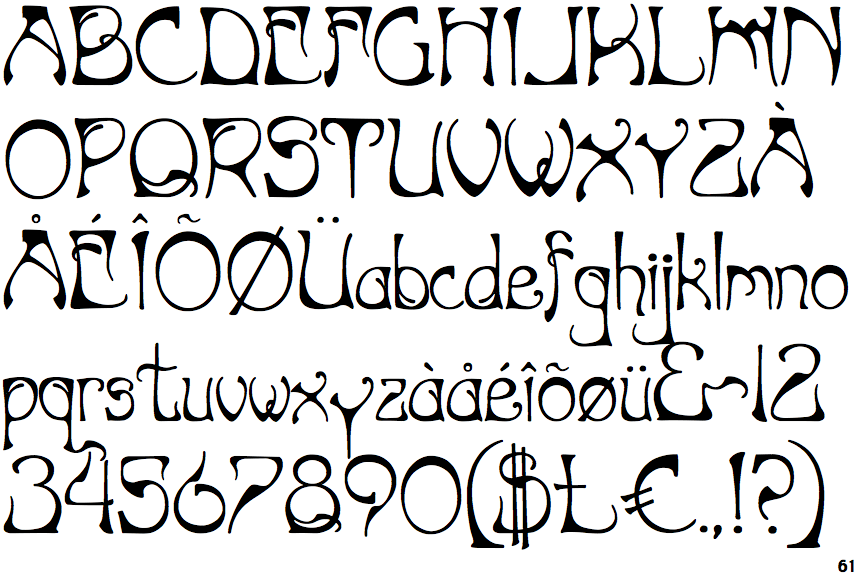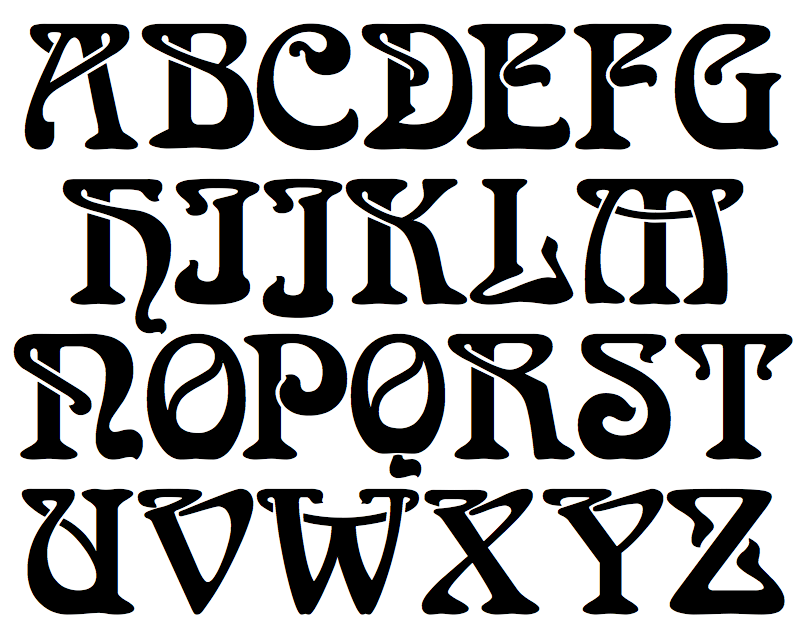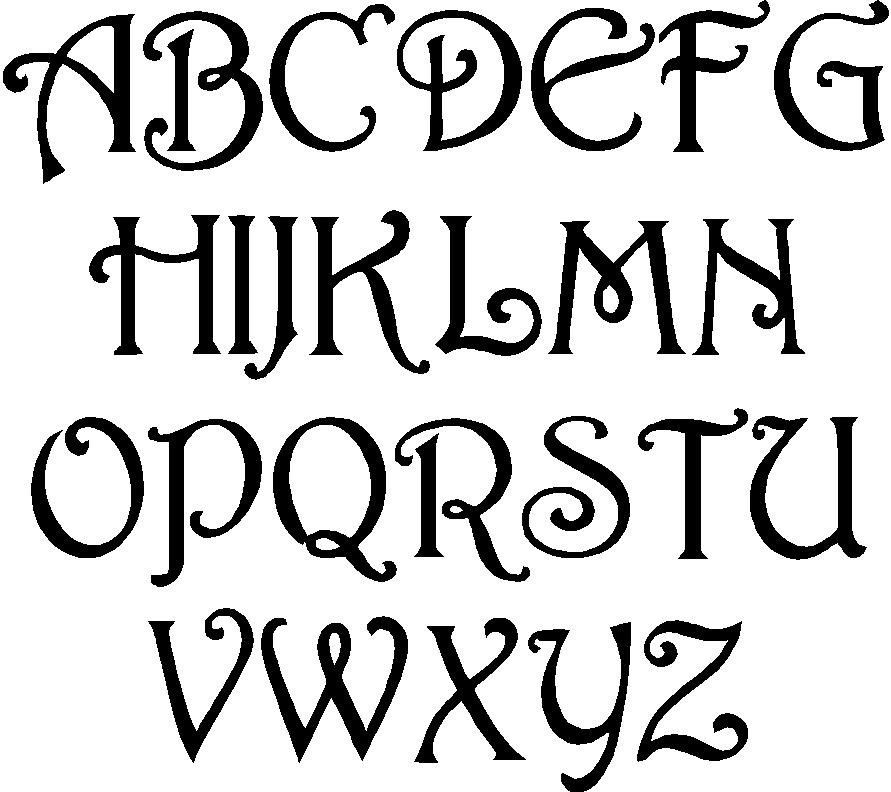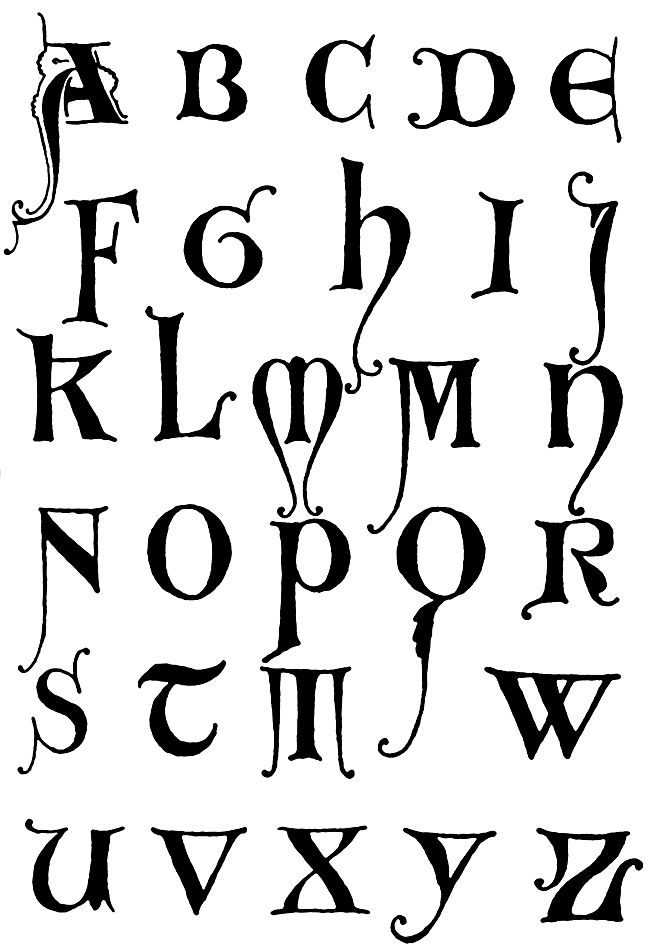
какие бывают и как выбрать
Шрифты для дизайна имеют первостепенную важность, ведь именно через них передаются настроение и голос любого креатива. Качество и изысканность дизайна во многом определяются выбранными шрифтами. К тому же не стоит забывать и об их прямой задаче – донесение информации до окружающих.
Таким образом, необходимость верного выбора шрифта очевидна, но для этого важно знать определенные правила. В нашей статье мы расскажем, какие их виды существуют и определим критерии, по которым стоит выбирать шрифты для проекта.
Понятие шрифта в дизайне
Термин «шрифт» в сфере дизайна применяется довольно часто. Чтобы лучше разобраться в данной теме, необходимо выделить три понятия: шрифт, гарнитура и вид шрифта.
Давайте подробно это рассмотрим.
- Гарнитура – это семейство начертаний шрифта, которые имеют общие стилевые особенности. Например, популярные Arial и Garamond – это гарнитуры, в которых присутствует набор различных вариантов: жирные, полужирные, курсивные и другие шрифты.
- Шрифт – это определенное начертание в рамках гарнитуры, а также файл со специальным разрешением, который нужно скачать на компьютер и установить в операционную систему. К примеру, Arial Italic и Garamond Bold являются шрифтами.
- Чтобы вам легче понять разницу в терминах, можете использовать такую аналогию: гарнитура – это фамилия, а шрифт – имя. К примеру, Helvetica – это общая фамилия одного семейства шрифтов, а Helvetica Neue Light будет именем конкретного шрифта.
- Начертание – это внешний вид шрифта, который определяет контраст и наклон написания букв. Часто дизайнеры используют один шрифт в его разных вариациях: обычный, жирный, легкий или курсивный, а также комбинируют с оттенками – легкий курсив или наоборот, супер жирный в обычном начертании.
- Вид шрифта – это группа из нескольких гарнитур, которую подбирает дизайнер по общим признакам. Например, несколько похожих гарнитур могут использоваться для написания заголовков, а декоративные шрифты – для красивого оформления текста.
Шрифты в дизайне можно разделять на виды и подвиды разными способами. Например, по времени их появления, по стилю написания букв, цели использования и многим другим параметрам.
Основные виды шрифтов для дизайна
Шрифты с засечками
К ним относятся шрифты, у которых буквы на конце имеют засечки — небольшие палочки. Этот вид шрифтов в дизайне представлен разнообразными стилями. Для примера можно взять известный Times New Roman. Профессиональный дизайнер или специалист в сфере типографики способен мгновенно определить, является ли шрифт с засечками классическим, или это современный вариант.
И здесь нет ничего удивительного: чтобы заметить разницу между ними, достаточно взглянуть на шрифты Sabon(классический) и Didot (современный).
Благодаря шрифтам с засечками текст в печатных материалах хорошо смотрится и его удобно читать. То же самое можно сказать о ситуациях, когда используется большое количество цифр.
Шрифты без засечек
Шрифты с засечками помогают информационным материалам передавать атмосферу новизны. Это свойство активно используют в рекламе, чтобы сделать акцент на проявлении чувств. А шрифты без засечек способны показать аудитории силу, стабильность и серьезность.
Чтобы в этом убедиться, можете взглянуть на традиционные шрифты News Gothic, Helvetica, Century Gothic и популярный Calibri. Их первоначальная форма содержала простые, толстые линии. По мере развития графического дизайна эти шрифты приобрели изящный, утонченный вид.
Брусковые шрифты
Говоря простыми словами, эти шрифты содержат очень маленькие и тяжелые засечки.
Как и шрифты без засечек, брусковые часто можно встретить в моноширинных шрифтах (когда каждая буква имеет одинаковую ширину). Ими люди активно пользуются на компьютерах и печатных машинках.
Например, набор текста с клавиатуры, часто производится в брусковых шрифтах Courier или Lucida Console.
Рукописные шрифты
Шрифты для дизайна появились не сами по себе — фактически, это имитация написания текста от руки. Классический рукописный шрифт имеет утонченный вид. Как правило, его буквы идут под наклоном. Новые рукописные шрифты смотрятся более красноречиво и содержат жирные начертания внутри гарнитуры.
Декоративные и акцидентные шрифты
Акцидентные шрифты в дизайне принято использовать, чтобы сделать текст как можно более заметным. Для написания основного контента они не подходят из-за громоздкости. Но для выделения некоторых слов и небольших заголовков акцидентный шрифт вполне уместен.
Декоративные шрифты присутствуют во всех гарнитурах. Они есть в шрифтах с засечками и без, рукописных и брусковых. Их основная особенность — это яркая выразительность и творческий подход.
Типичные представители этого вида — декоративные шрифты Broadway, Bauhaus и Windsor.